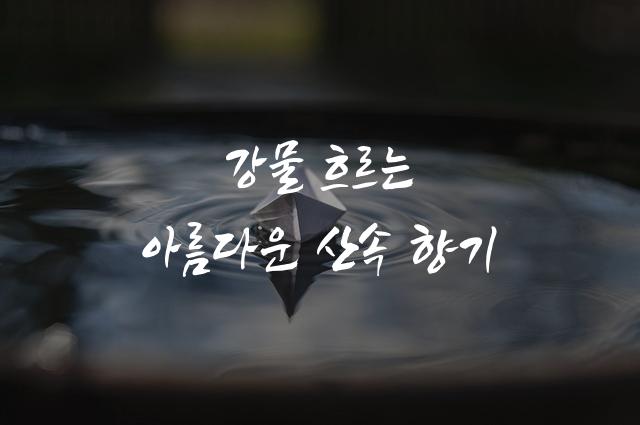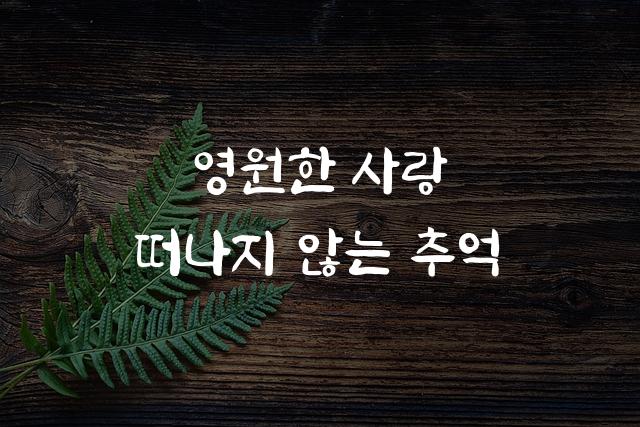
정선아리랑뿌리체는 전통적인 붓글씨 스타일을 현대적으로 재해석한 캘리그라피 폰트입니다. 고전의 멋과 현대의 감각이 어우러져 감성적인 디자인을 완성합니다.
정선아리랑뿌리체은(는)
손글씨, 명조/전통, 펜/붓터치, 감성적인, 복고풍 계열의 생김새를 가지고 있으며
웹/앱 디자인, 출판 디자인, 출판물 제목 등에서 자주 활용되며, 효과적인 메시지 전달에 적합합니다.
이 폰트는 출판/미디어, 문화/예술, 공공/정부 분야에 잘 어울리며,
전통적, 편안한, 클래식한 느낌을 담고 있는 것이 특징입니다.